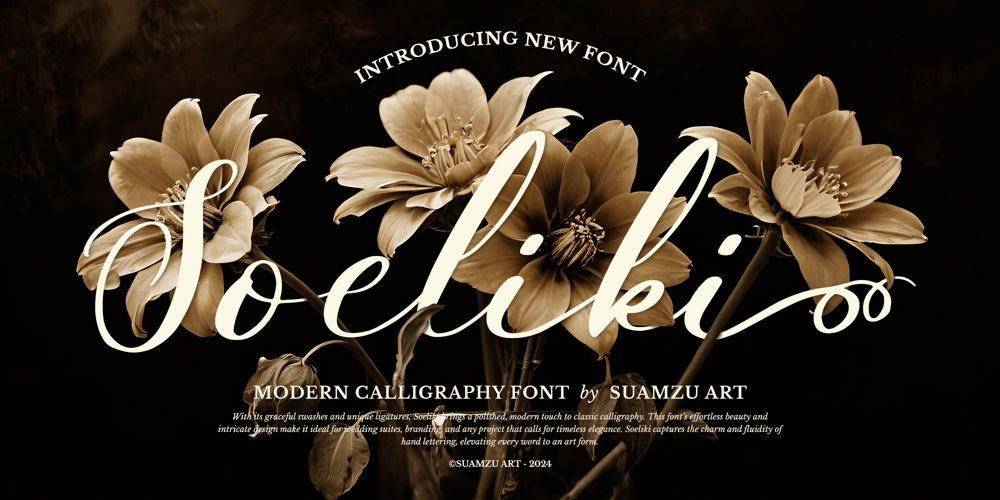
Soeliki Font Family was designed by Amrullah Medan, Amrullah and published by Suamzu Art. Soeliki contains 1 styles and family package options. Soeliki adalah font script yang dirancang khusus untuk menghadirkan sentuhan keindahan dan keanggunan alami dalam setiap hurufnya. Dengan gaya yang mengalir lembut, Soeliki sangat ideal untuk desain acara wedding, menciptakan nuansa romantis yang memikat. Setiap huruf disusun dengan detail yang elegan dan konsisten, dilengkapi dengan beberapa alternatif huruf untuk memberikan variasi yang lebih personal dan kreatif. Font ini sempurna untuk logo wedding yang memancarkan kemewahan tanpa kehilangan sentuhan keintiman, serta brosur wedding yang ingin menyajikan kesan eksklusif namun tetap hangat. Soeliki menggabungkan keindahan klasik dengan kehalusan modern, membuatnya ideal untuk undangan, dekorasi, dan semua elemen visual yang berhubungan dengan momen spesial pernikahan. Soeliki adalah pilihan tepat bagi desainer yang ingin menghadirkan gaya script yang natural dan timeless di setiap detail pernikahan.